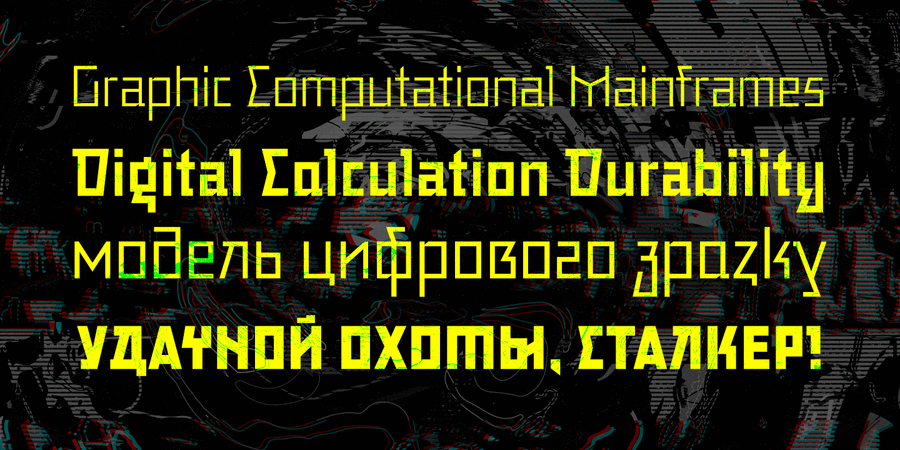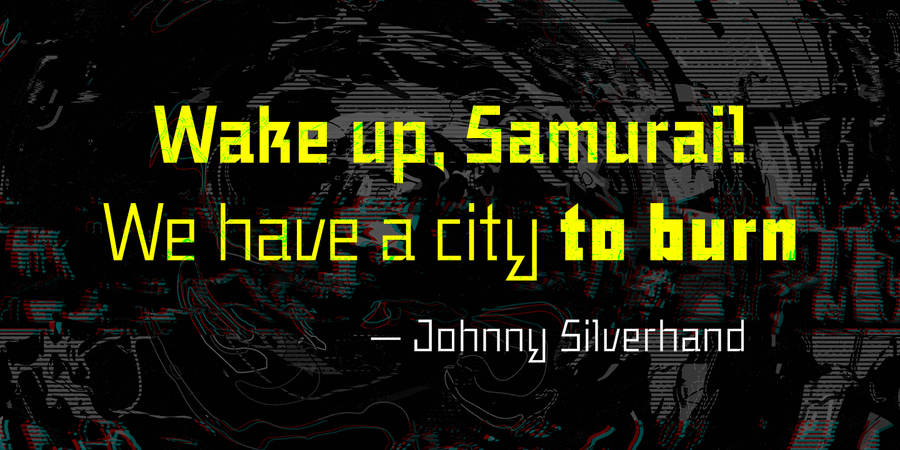
Опис гарнітури LegasovЛегасов – это оригинальное шрифтовое семейство, предназначенное для логотипов, заголовков, обложек книг и фирменного стиля. Вы также можете использовать его для небольших текстовых фрагментов. Легасов – современный палочный геометрический гротеск, вдохновленный украинским модернизмом 20-го века. Он имеет динамичную форму знаков и авангардный характер. Шрифт разработали Сергей Макаренко и Кирилл Ткачев в 2022 году.
Особливості сімейства шрифтів LegasovХіт десятиліття:
Асоціації з сімейством шрифтів LegasovОсобистість і характер гарнітури:
твердий, точний, впевнений, сталевий, рівний, стійкий, холодний, машинний, гострий, тонкий, урбаністичний, міський, скляний, крижаний, надійний, рубаний, серйозний, переконливий, залізний, мужній, ностальгічний, тоталітарний, стабільний, гучний, сильний, кондовий, політичний, комуністичний, революційний, сміливий, пролетарський, прямокутний, індустріальний, техногенний, військовий, армійський, солдатський, грубий, робочий, мотивуючий, залізничний, амбітний, незграбний, жорсткий, ламаний, елементарний, різкий, чіткий, брутальний, ігровий, міцний, важкий, авторитетний, значний, важливий, червоний, монументальний, суворий, блатний, крутий, кричущий, радикальний
конструктор, креслення, архітектура, урбаністика, коворкінг, Місто, війна, армія, зброя, машинобудування, прапор, політика, шахта, завод, металургія, верстат, інструмент, будівництво, будматеріали, тара, склад, порт, ящик, патрони, техніка, промисловість, електростанція, енергетика, ремонт, депо, шахтар, шолом, уніформа, вагон, авіація, літак, страйкбол, взуття, залізниця, робочий, страйк, кубики, лего, мітинг, Протест, танк, тренажери, революція, блокбастер, бойовик, екшен, цегла, вантажівка, далекобійник, мотор, двигун, реп, концерт, селфі Гарнітура асоціюється з віком: